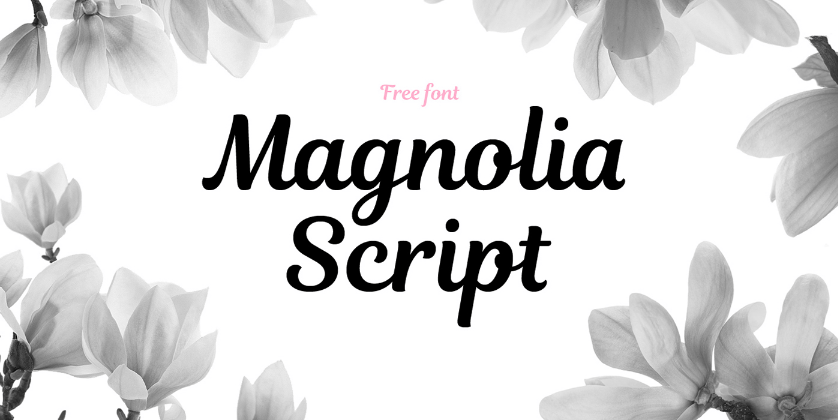
Vstoupili jste právě na pole neprozkoumané. Ať jsem hledala, jak jsem hledala, nikde ve vodách českého internetu jsem nenašla ani zmínku o tom, že by se někdo zkoumal, jaký má vliv výběr fontů (písma) v textu na podvědomí čtenářů. Přitom je běžný pojem psychologie barev, nebo grafologie. Ano, na počítači  nepíšete vlastní rukou, ale vnímáte tvary písmen, mezery mezi nimi i vzájemné proporce čar a křivek. To vše na vás působí a vyvolává ve vás emoce.
Stalo se vám někdy, že jste nekoupili knihu, protože vás obálka nezaujala, nebo dokonce odpudila? Třeba to byl nevhodný obrázek, ale třeba to byl právě nevhodný font. Možná, kdybyste se nad tím zamysleli a analyzovali obálku, pojmenovali byste správně tu špatnou emoci, kterou ve vás vzbudil.
Phil Renaud, kanadský student na univerzitě, zkoumal, proč dostane z eseje jednou výrazně lepší známku než jindy, když úroveň zpracování je stejná. Zjistil, že jediná věc, která se výrazně změnila, byl font. Rozdělil eseje podle použitého fontu a průměrná známka za každou kopičku se výrazně lišila.
„ Možná, že font má mnohem větší význam, než si myslíme.“
Novinář E.Morris podnikl marketingový experiment, ve kterém sledoval, nakolik změna fontu ovlivní důvěryhodnost textu.
„ Můžeme oddělit formu a obsah textu?“
Zjistil, že vybraný font má obrovskou moc ovlivnit vnímání čtenářů. Vyberete seriózní font, věří vám. Vyberete Comic sans a důvěra v pravdivost informací v textu klesne o polovinu.
Tento úzký vztah mezi podvědomím lidí a fontem, který si vybírají, mne fascinuje. Po mnoha konzultacích Profil podle fontu mohu zodpovědně prohlásit, že font je jako oblečení. Dokonale popíše váš charakter. A je škoda, když vám nepadne.
A tak na svém webu učím lidi, jak neoblékat text pouze do riflí, nebo dokonce tepláků. Jak mu vybrat oblečení podle vlastního charakterui, a jak díky tomu vyniknout a působit autenticky. Že má svůj význam opustit Arial a Calibri a vybírat na různé příležitosti různé fonty.
Abych vám ukázala praktické příklady, zpracovala jsem e-book zdarma, pro který jsem vybrala jsem 5 fontů a popsala jejich charakter, kdy je vhodné je použít a jak budou působit na čtenáře. Jsou to velmi rozdílné fonty, nepočítejte s tím, že se vám budou líbit všechny. Naopak. Jsou vybrané tak, aby každý z nich oslovil jinou skupinu lidí. Font Mangnolia osloví zejména elegantní ženy s osobností, font Summer svou přátelskostí téměř každého a font Muller Narrow praktické duše a minimalisty. Mohou se vám líbit i dva z nich, třeba jste přátelský minimalista. 🙂
Možná se vám font Magnolia, který v něm najdete, nelíbí, je na vás moc kudrlinkatý, to je v pořádku. Možná také nenosíte sukně každý den. Ale když půjdete na svatbu, nebo ples, tak si sukni vezmete, že? Tak až příště budete psát článek určený ženám, které jsou elegantní a přitom něžné, použijte na nadpis tento font. Uvidíte, že je osloví daleko více, než Calibri.